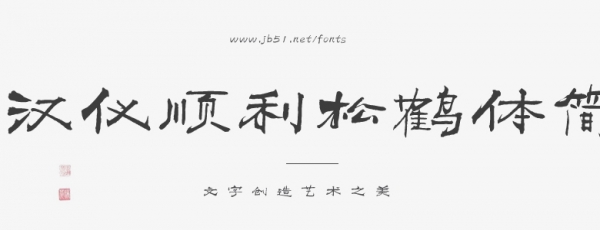
漢儀順利松鶴字體采用了傳統(tǒng)毛筆書(shū)法的手寫(xiě)風(fēng)格,使其具有形神兼?zhèn)?,?shū)法優(yōu)美的特點(diǎn)。其字形流暢,線條優(yōu)美,裝飾性強(qiáng),適用于書(shū)法創(chuàng)作、印刷設(shè)計(jì)、文學(xué)、包裝設(shè)計(jì)等領(lǐng)域,能夠滿足不同的設(shè)計(jì)需求。